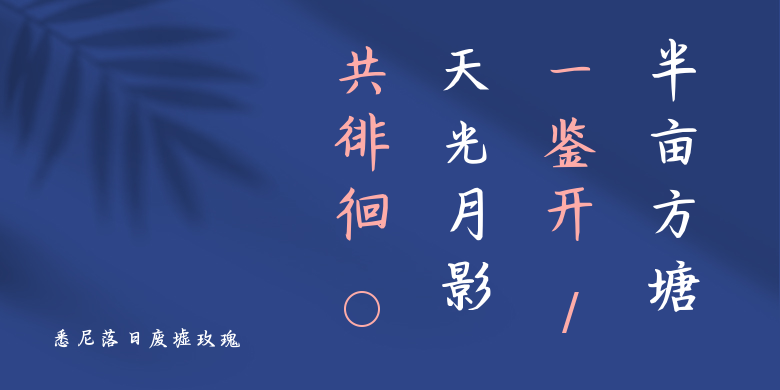
悉尼落日废墟玫瑰
悉尼落日废墟玫瑰,这款字体结构工整、笔画清晰,兼顾美观与易读性,适用于标题、正文、海报、包装、LOGO 等多种场景。字形优雅稳定,风格百搭耐看,适配日常排版与创意设计,让文字呈现更舒适、更具质感。悉尼落日废墟玫瑰一笔一画,皆是细节,以均衡的比例、流畅的线条打造舒适视觉体验,字形端正大气,风格简约现代。无论是商业设计、品牌宣传还是日常排版,都能轻松驾驭,让文字更有格调与力量。悉尼落日废墟玫瑰字体下载。